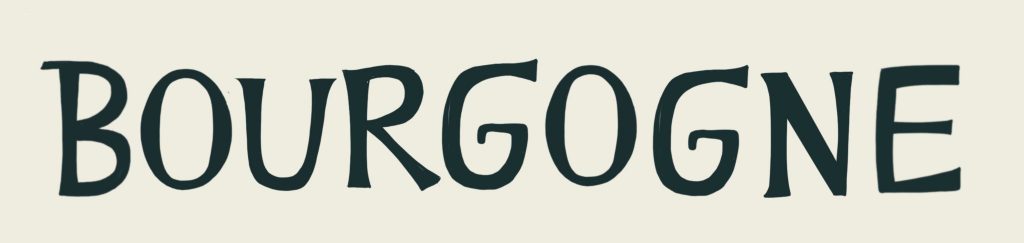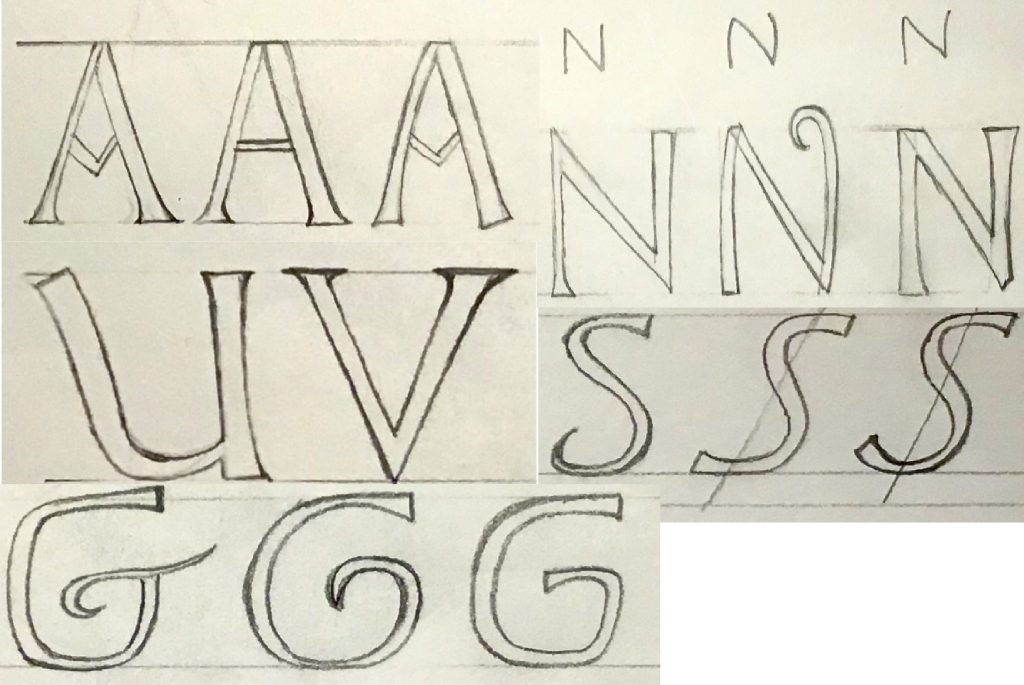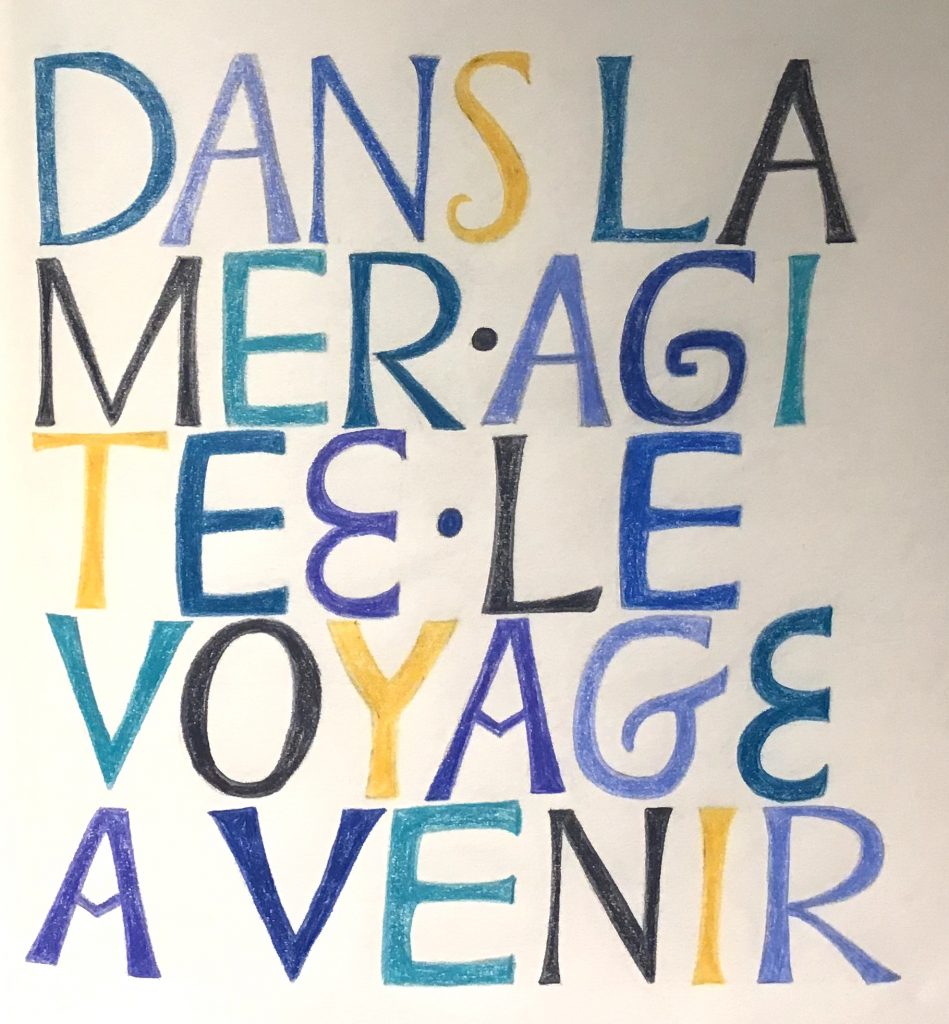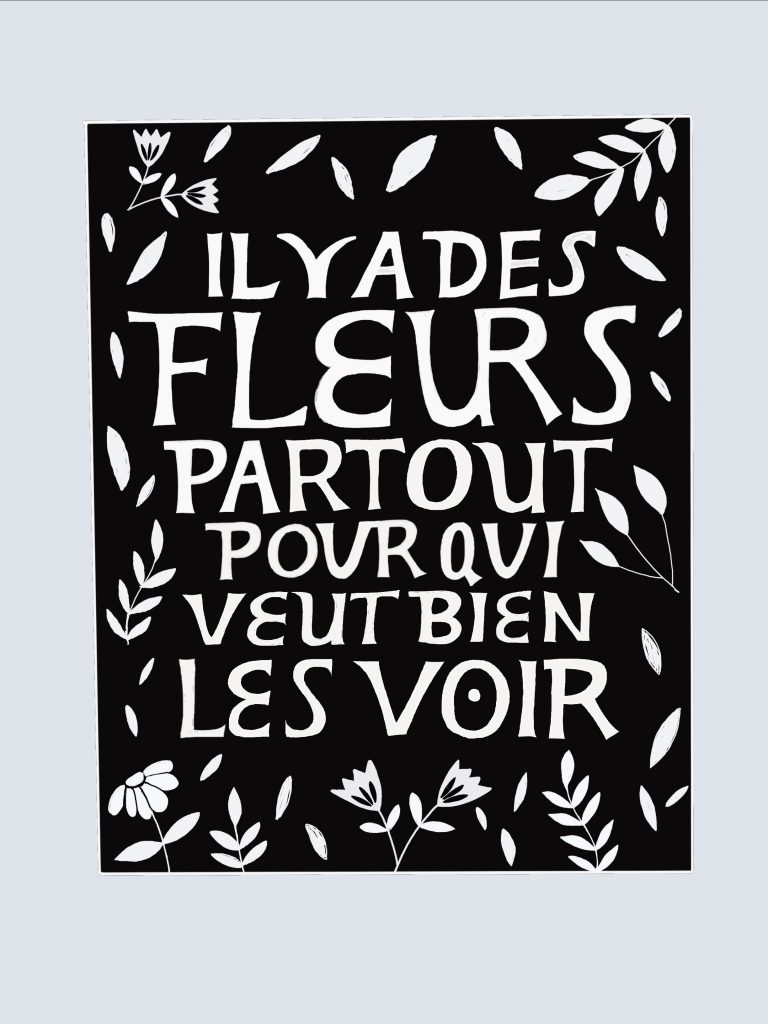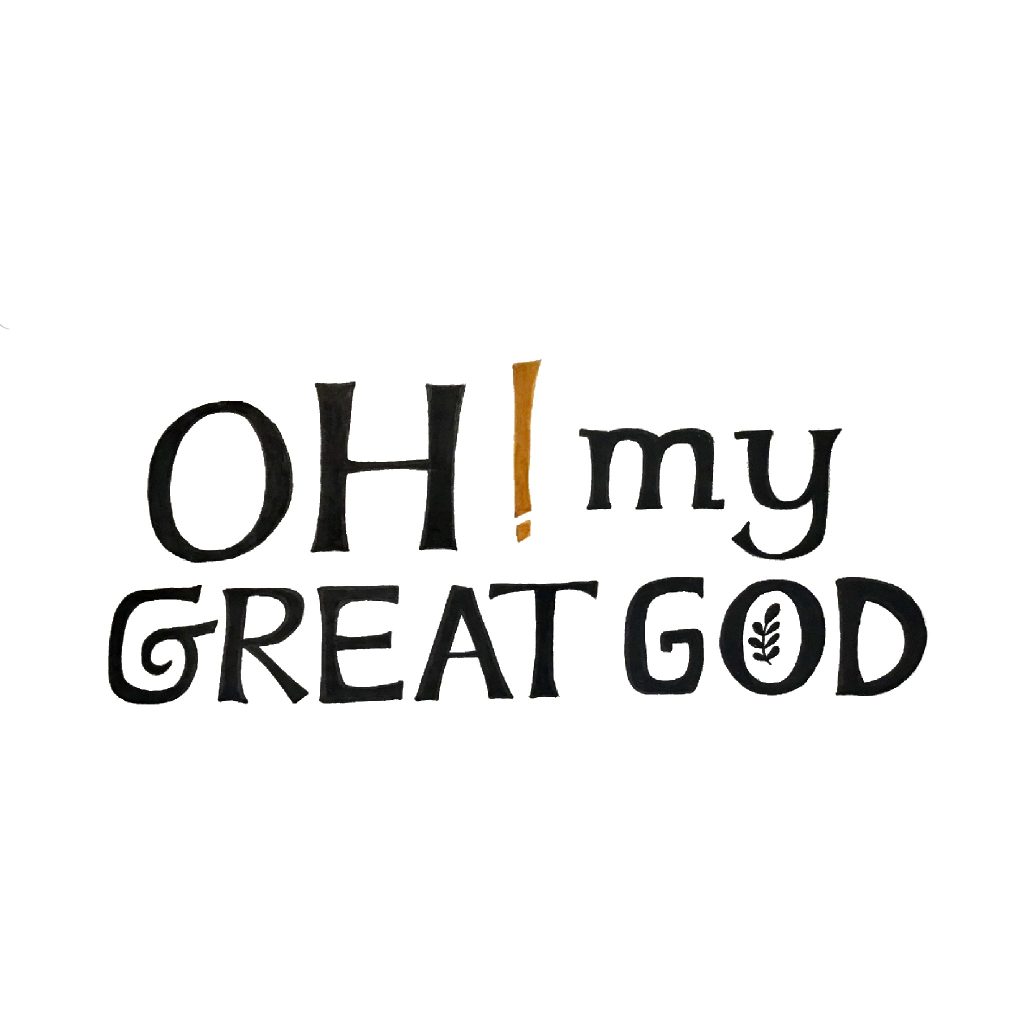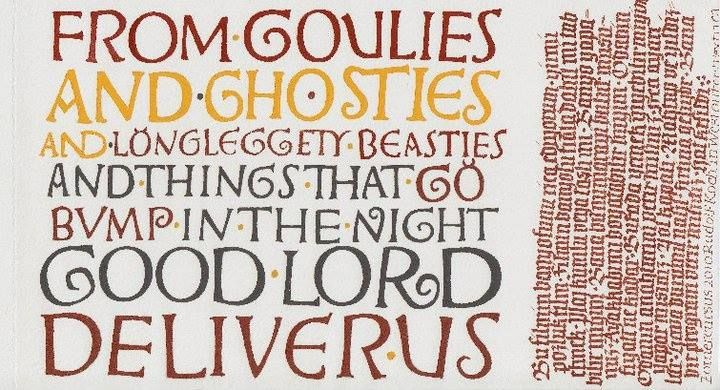
David Jones (1895-1974) était un artiste anglais aux multiples facettes : poète, peintre, essayiste, graveur de caractères, il est connu dans le monde de la calligraphie pour son travail de lettrage unique et singulier. Inspiré par les inscriptions romaines gravées dans la pierre et par les manuscrits anciens,  il travailla les lettres capitales de façon naïve et un peu simplifiée, tout en leur conservant une dynamique propre et une certaine musicalité. Au-delà de la lettre elle-même, il a travaillé la composition avec un intérêt particulier pour la façon dont les lettres et les mots tissent un ensemble rythmé et cohérent.
C’est en observant le travail de calligraphes américains, anglais et belges que je suis venue à découvrir leurs inspirations issues du travail de David Jones. Je crois que ce qui m’a touchée dans ce travail c’est l’interprétation naïve, un peu enfantine mais résolument moderne de ces écritures anciennes.
Comme on ne parle de cet artiste dans aucun de mes livres de calligraphie, j’ai fait quelques recherches et je vous propose une petite découverte.
Inspirations et recherches
Pour aborder le travail de David Jones, revenons à la source de ses inspirations : la gravure lapidaire romaine et les manuscrits anciens.
Dans l’exemple de bloc gravé ci-dessous on observe des capitales, certes, mais moins formelles que dans certains exemples de gravures plus tardives où les lettres seront parfaitement calibrées et espacées.
Exemple de gravure romaine – British Museum
Dans les manuscrits anciens, on trouvera de riches exemples d’utilisation des capitales romaines et onciales, comme dans le manuscrit ci-dessous daté du 12ème siècle. Elles étaient utilisées en « frontipice », c’est à dire en titre d’un chapitre. Remarquez le côté à la fois formel et libre de la composition de ce frontipice : ce n’est pas, a priori, un choix artistique pur, mais plutôt une volonté d’optimiser l’occupation de la page. Cela a fait recourir les moines à des astuces créatives, comme l’insertion de lettres dans d’autres comme dans le mot INCIPIT.
Remarquez aussi l’utilisation des couleurs.
Alençon BM0644 – 12ème siècle
Autre exemple de frontipice, manuscrit anglais du 12ème siècle, mixant harmonieusement la capitale romaine formelle et les onciales.
Le travail de David Jones
David Jones est donc allé puiser dans les manuscrits anciens et les gravures lapidaires les lettres qu’il a ensuite réinterprétées. Ces lettres proviennent de la capitale romaine et des onciales
Les lettres sont dessinées au crayon puis peintes. Comme dans les manuscrits, David Jones utilisait jusqu’à 3 couleurs.
Les caractéristiques remarquables du travail de David Jones
Planche de David Jones, caractéristique de son oeuvre.
• Contrairement aux capitales romaines formelles, les lettres de Jones sont moins droites, moins rigides. La forme est souple, un peu arrondie, cintrée et élancée… mais certainement pas molle !
• Les empattements sont souvent présents, comme s’ils ouvraient la lettre sur l’extérieur.
• A défaut d’empattement, on trouve parfois des terminaisons en boucles, commes celles utilisées dans le manuscrit anglais plus haut.
• Une lettre peut être réalisée de différentes façons : c’est aussi ce qui apporte le rythme et la musicalité à l’ensemble.
• Des ligatures sont parfois créées entre les lettres : pour enrichir le rythme ou pour optimiser l’agencement de la ligne.
• Les espaces sont parfois matérialisés par des points
Composition
Ce qui caractérise la composition c’est vraiment le côté dansant, un peu naïf et faussement libre. Je dis faussement libre, car :
• Les lettres ne sont pas strictement alignées
• D’une ligne à l’autre, la taille varie
• Malgré tout, l’ensemble ne choque pas l’œil car Jones joue énormément sur les contreformes (les formes à l’extérieur de la lettre) pour gérer l’espace dans son ensemble
Appropriation et essais personnels
Observation et dessin des formes caractéristiques
C’est la première étape : le dessin. J’ai commencé par observer les réalisations de David Jones et suis partie en quête des différentes interprétations des lettres.
Notez par exemple les différentes courbes du N, les terminaisons en boucle, l’axe du S, les versions du U, l’ouverture de la lettre G…
Quelques réalisations
L’exemple ci-dessus, Bourgogne, a été réalisé sur Ipad. C’était bien pratique pour ajuster les proportions et l’espacement des lettres, chose que j’ai trouvée difficile au début.
Citation de Matisse
Fait au feutre fin, initialement pour faire une linogravure, avec en sus la difficulté de travailler en négatif (donc de colorier autour des lettres). Ça commence à se rapprocher un peu plus de l’esprit David Jones, notamment avec l’exploitation de plusieurs formes pour une même lettre et l’utilisation de ligatures.
C’est malgré tout assez loin des modèles historiques, les lettres sont très stylisées.
Il m’a fallu plusieurs brouillons et beaucoup de gomme pour trouver un équilibre d’ensemble.
Haiku au crayon de papier
Plus proche des modèles historiques, avec une bonne balance dans la composition. Je regrette juste le choix du crayon de couleur : la gouache aurait été plus « clean », plus contrastée.
En plus, suivant tes choix de mise en page, tu peux créer une illustration seulement avec des caractères.
Bref, pour commencer le lettering c’est parfait.